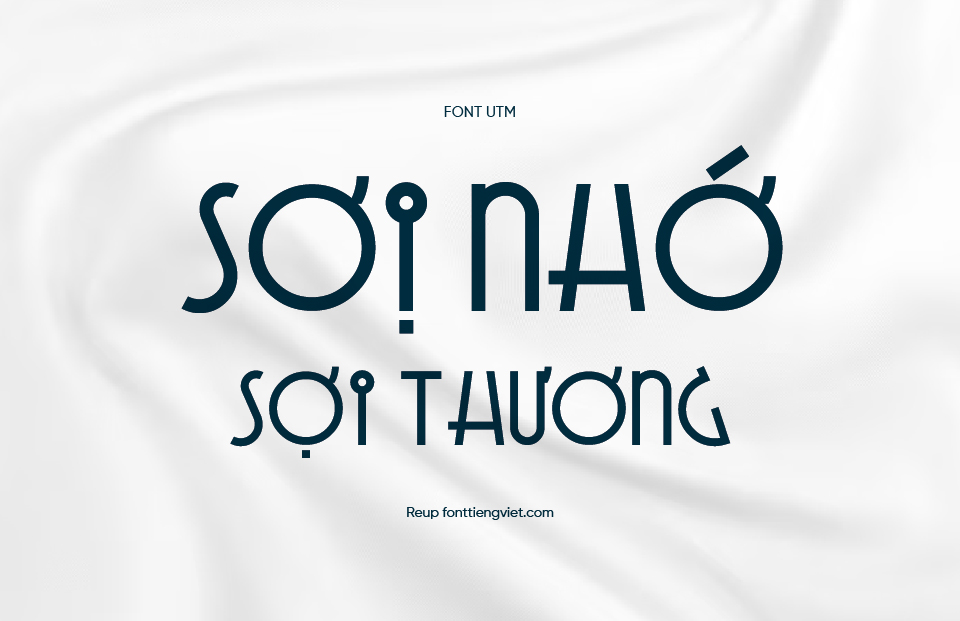
Font Việt hóa UTM Gradoo
Giới thiệu về Font Việt hóa UTM Gradoo
Trong thế giới thiết kế đồ họa hiện đại, việc lựa chọn một Font Miễn Phí chất lượng luôn là ưu tiên hàng đầu của các nhà sáng tạo. Font Việt hóa UTM Gradoo nổi lên như một lựa chọn hoàn hảo nhờ sự kết hợp tinh tế giữa nét chữ cổ điển và phong cách hiện đại. Đây là bộ phông chữ thuộc dòng UTM nổi tiếng, đã được điều chỉnh kỹ lưỡng để phù hợp hoàn toàn với bảng mã tiếng Việt, giúp người dùng không còn lo lắng về lỗi hiển thị dấu hay khoảng cách ký tự không đều.
Ưu điểm nổi bật của Font Việt hóa UTM Gradoo
Thiết kế thanh lịch và linh hoạt
Đặc điểm nhận dạng của Font Việt hóa UTM Gradoo chính là những đường nét thanh mảnh nhưng vô cùng dứt khoát. Bộ chữ này mang lại cảm giác chuyên nghiệp, trang nhã, cực kỳ thích hợp cho các dự án thiết kế thiệp mời, bìa sách hoặc tiêu đề tạp chí. Với độ tương phản nhẹ nhàng, font chữ giúp nội dung trở nên dễ đọc và bắt mắt hơn trên cả nền tảng in ấn lẫn kỹ thuật số.
Ứng dụng đa dạng trong thực tế
Bạn có thể sử dụng bộ phông này cho nhiều mục đích khác nhau như làm banner quảng cáo, thiết kế logo thương hiệu hay trình bày slide thuyết trình. Tính ứng dụng cao giúp nó trở thành công cụ đắc lực cho sinh viên và các nhà thiết kế tự do tại Việt Nam khi muốn tạo ra những tác phẩm có chiều sâu nghệ thuật mà vẫn giữ được sự rõ ràng.